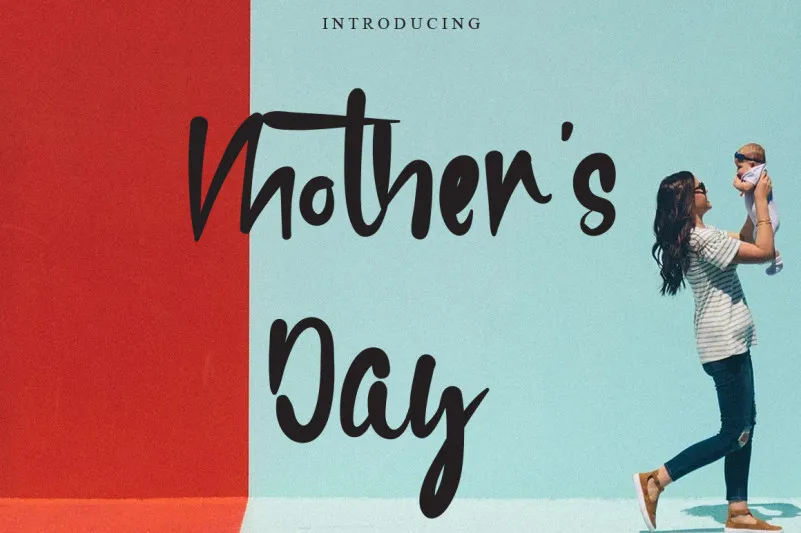
Mother’s Day Font – Download Grátis
Esta é uma fonte escrita a mão única e exclusiva. Ideal para qualquer projeto de design que busque uma aparência encantadora! Com sua textura natural e personalidade quase que irresistível, essa fonte se destaca entre as demais, seja em cartões de aniversário criativos, letras fortes em materiais impressos ou até mesmo em projetos digitais. Como designer levincreative, criamos algo a mais para você, uma fonte escrita a mão capaz de trazer um toque especial à sua próxima criação visual. Seja qual seja o seu próximo projeto, permita que essa fonte maternal dê vida e charme ao seu trabalho!